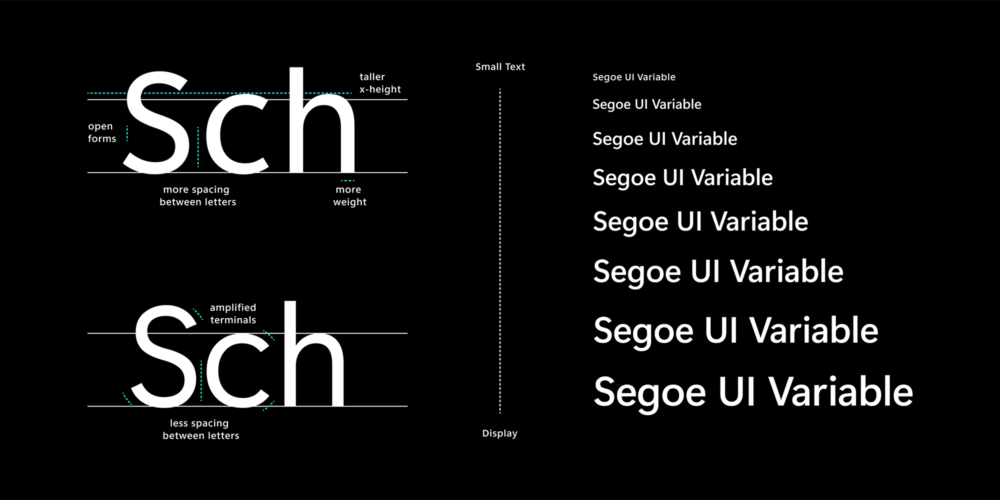
Najnowsza eksperymentalna wersja Windowsa 10 to między innymi zmieniony wygląd czcionki Segoe UI Variable. Tak się składa, że czcionka ta ma być również domyślną dla całego systemu operacyjnego.
W kanale Windows Insider Dev pojawiła się nowa, eksperymentalna wersja Windowsa 10. Czemu eksperymentalna? Dla przypomnienia: kanał Dev służy do testowania nowości, które mogą – choć nie muszą – trafić do jednej z przyszłych wersji systemu Microsoftu. Tyle że tym razem Microsoft zdaje się być przekonany do swojego pomysłu. A jest nim uaktualnienie czcionki Segoe UI Variable, która jest domyślną dla windowsowego interfejsu.
Domyślna czcionka dla przyszłych wersji Windows 10 to uaktualniona Segoe UI Variable. Skąd ta zmiana?
Jak tłumaczy Microsoft, nowa czcionka dużo lepiej skaluje się na wyświetlaczach różnych rozmiarów. Segoe UI została zaprojektowana z myślą o byciu wyświetlaną w rozmiarze 9 pkt. Jednak – jak twierdzą projektanci Windowsa – nie jest dostatecznie wydatna po powiększeniu i nie jest dostatecznie czytelna w mniejszych rozmiarach.
Segoe UI Variable w swojej najnowszej wersji jest już zaimplementowana w kompilacji systemu o numerze 21376. Microsoft zaznacza, że jeszcze nie wszystkie elementy w systemie ją wykorzystują, co ma się zmienić w przyszłych testowych kompilacjach. Oby tylko zdążyli do najbliższej aktualizacji rozwojowej produkcyjnej wersji systemu. Premiera Windowsa 10 21H2 spodziewana jest na jesień bieżącego roku.